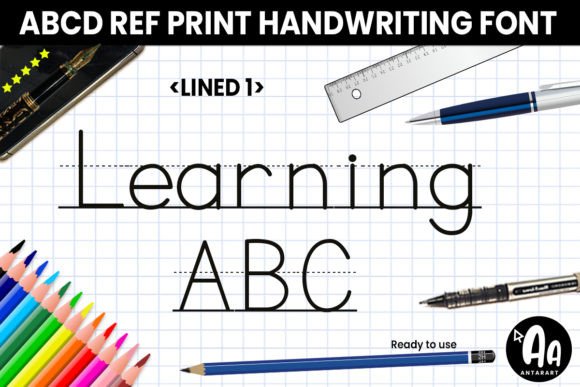
Abcd Ref Lined1
Jika anda sedang mencari aset berkualiti tinggi seperti Abcd Ref Lined1, pakej premium ini merupakan pilihan yang hebat untuk projek kreatif anda.
Dicipta dengan ketepatan, Abcd Ref Lined1 menyediakan vektor yang bersih, tipografi yang licin dan lesen komersial untuk ketenangan fikiran.
Sama ada anda mencipta produk POD (Print on Demand), jemputan perkahwinan atau grafik media sosial, Abcd Ref Lined1 amat bersesuaian.